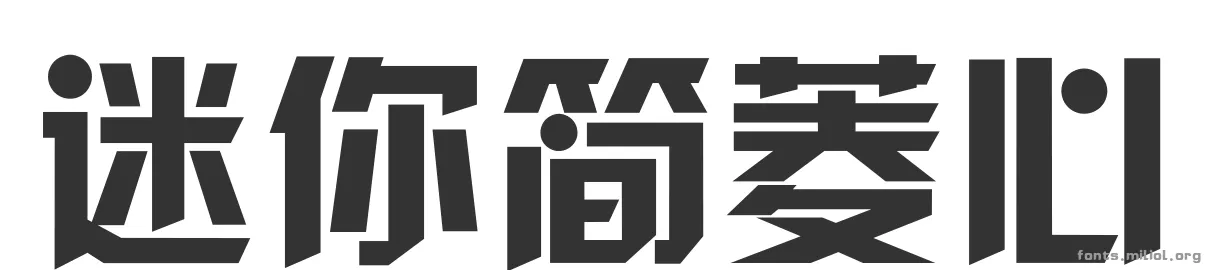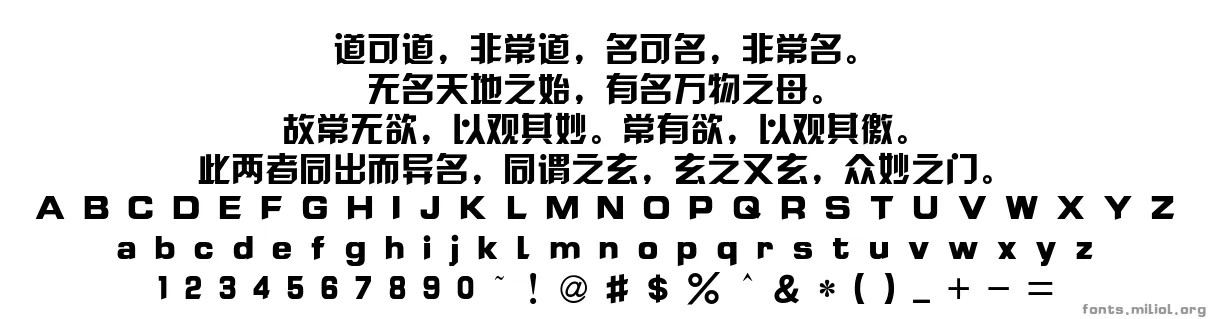
**迷你简菱心 (JLinXin) 字体:优雅与个性的融合**
迷你简菱心(JLinXin)是一款兼具现代感与艺术气息的中文字体,以其独特的笔画设计和流畅的线条深受设计师和文字爱好者的青睐。这款字体在保留传统汉字结构的基础上,融入了菱形的几何元素,使整体视觉效果既简洁又不失个性,特别适合用于标题、广告、品牌标识等需要突出设计感的场合。
JLinXin字体的笔画干净利落,转折处带有微妙的棱角,既不会过于锋利,又能展现出鲜明的风格。其清晰的可读性使其在印刷品和数字媒体上均能表现出色,无论是海报、包装还是网页设计,都能为作品增添独特的视觉魅力。
作为一款免费字体,迷你简菱心为创意工作者提供了更多可能性,让文字不再只是信息的载体,更成为设计的一部分。无论是商业项目还是个人创作,它都能帮助用户轻松打造出兼具美感和辨识度的视觉语言。